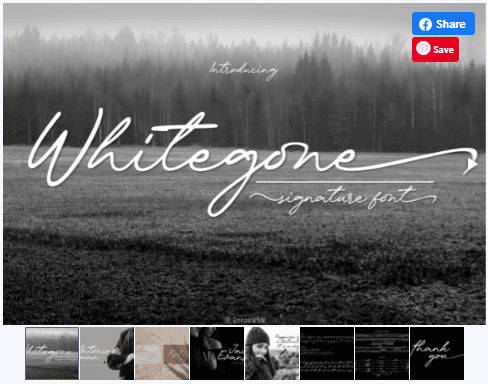
Whitegone Font
Whitegone - прекрасный и неподвластный времени рукописный шрифт. Это лучший выбор для создания привлекательных логотипов, брендов и цитат. Каждая буква имеет уникальный и красивый штрих, который оживит ваш дизайн. Этот шрифт закодирован в кодировке PUA, что означает, что вы можете легко получить доступ ко всем глифам и штрихам!